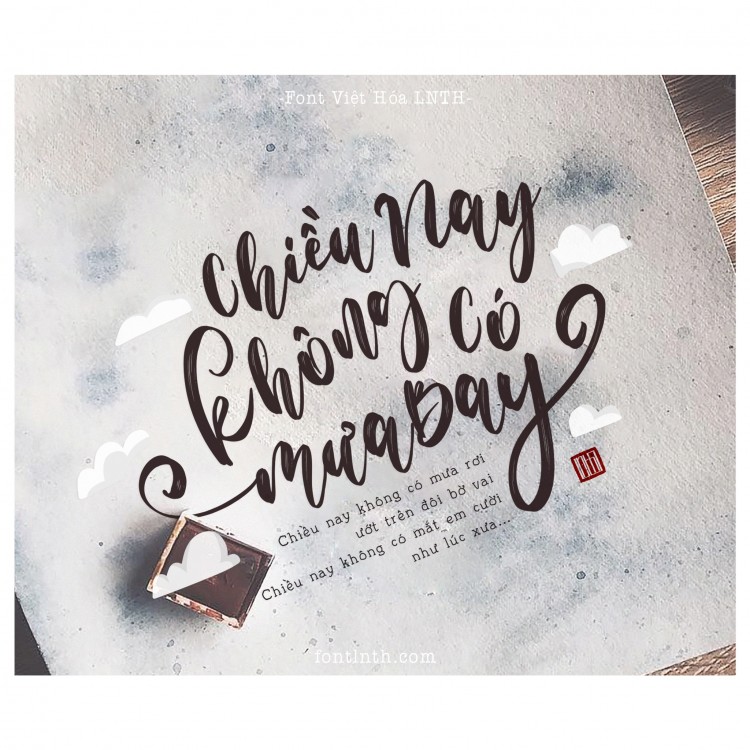
Giới thiệu về bộ Font việt hoá LNTH Flower Winter
Trong thế giới đồ họa hiện đại, việc tìm kiếm một mẫu Font Chữ mang phong cách mềm mại và ấm áp luôn là ưu tiên hàng đầu của các nhà thiết kế. Font việt hoá LNTH Flower Winter là một lựa chọn tuyệt vời dành cho những ai yêu thích sự kết hợp giữa nét vẽ tay uyển chuyển và tinh thần lãng mạn của mùa đông. Bộ phông này đã được tối ưu hóa bảng mã tiếng Việt, giúp bạn dễ dàng sử dụng trên mọi phần mềm thiết kế mà không lo lỗi hiển thị.
Đặc điểm nổi bật của Font việt hoá LNTH Flower Winter
Thiết kế bay bổng và tinh tế
Đúng như tên gọi, Font việt hoá LNTH Flower Winter mang đến cảm giác nhẹ nhàng như những cánh hoa rơi trong tuyết. Các đường nét được chăm chút kỹ lưỡng, tạo nên sự cân bằng hoàn hảo giữa tính thẩm mỹ và khả năng đọc hiểu. Đây là lựa chọn lý tưởng cho các bạn học sinh thực hiện báo tường, làm thiệp chúc mừng hay trang trí slide thuyết trình tại trường học.
Tính ứng dụng đa dạng trong thực tế
Nhờ phong cách Script đặc trưng, bộ font này cực kỳ phù hợp cho các dự án thiết kế bao bì, logo thương hiệu handmade hoặc các ấn phẩm truyền thông trên mạng xã hội. Sự mềm mại của nó giúp thông điệp truyền tải trở nên gần gũi và giàu cảm xúc hơn đối với người xem.
Kết luận và tải xuống